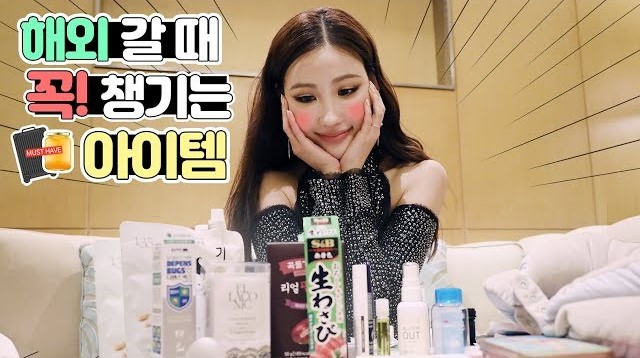
여기어때 잘난체 — 여기어때컴퍼니에서 배포하는 무료 폰트입니다. 꽉 찬 네모꼴에 경쾌한 곡선과 독특한 자소를 더한 개성 강한 고딕체
여기어때가 2018년 한글날 하루 전에 공개한 서체로, 산돌커뮤니케이션이 제작했습니다.
모티브가 브랜드 곳곳에서 왔습니다. 제작사는 여기어때 로고와 닮은 구조의 곡선과 직선의 조화라고 설명하면서, 라운드와 직선을 모두 담은 모음과 곡선으로 떨어지는 자음을 특징으로 꼽습니다. 여기에 ㅅ과 ㅈ, ㅊ처럼 두 획이 교차하는 자음을 뛰는 사람 형상으로 표현했고, 마스코트 콩이를 딩벳 열 종으로 넣어 두었습니다. 파일에서 재어 보면 자면을 채우는 비율이 높아 굵고 진한 인상을 냅니다.
제목 전용으로 만들어져 썸네일과 배너, 웹툰 표지, 영상 자막에 널리 쓰입니다. 굵기가 하나이고 개성이 강해 긴 본문에는 맞지 않는데, 정보 전달이 우선인 자리라면 2023년에 나온 자매 서체 잘난체 고딕 쪽이 낫습니다. 무료로 상업적으로 쓸 수 있고 CI와 BI에도 허용되지만, 폰트를 유료로 팔거나 임의로 고쳐 재배포하는 것은 금지됩니다.